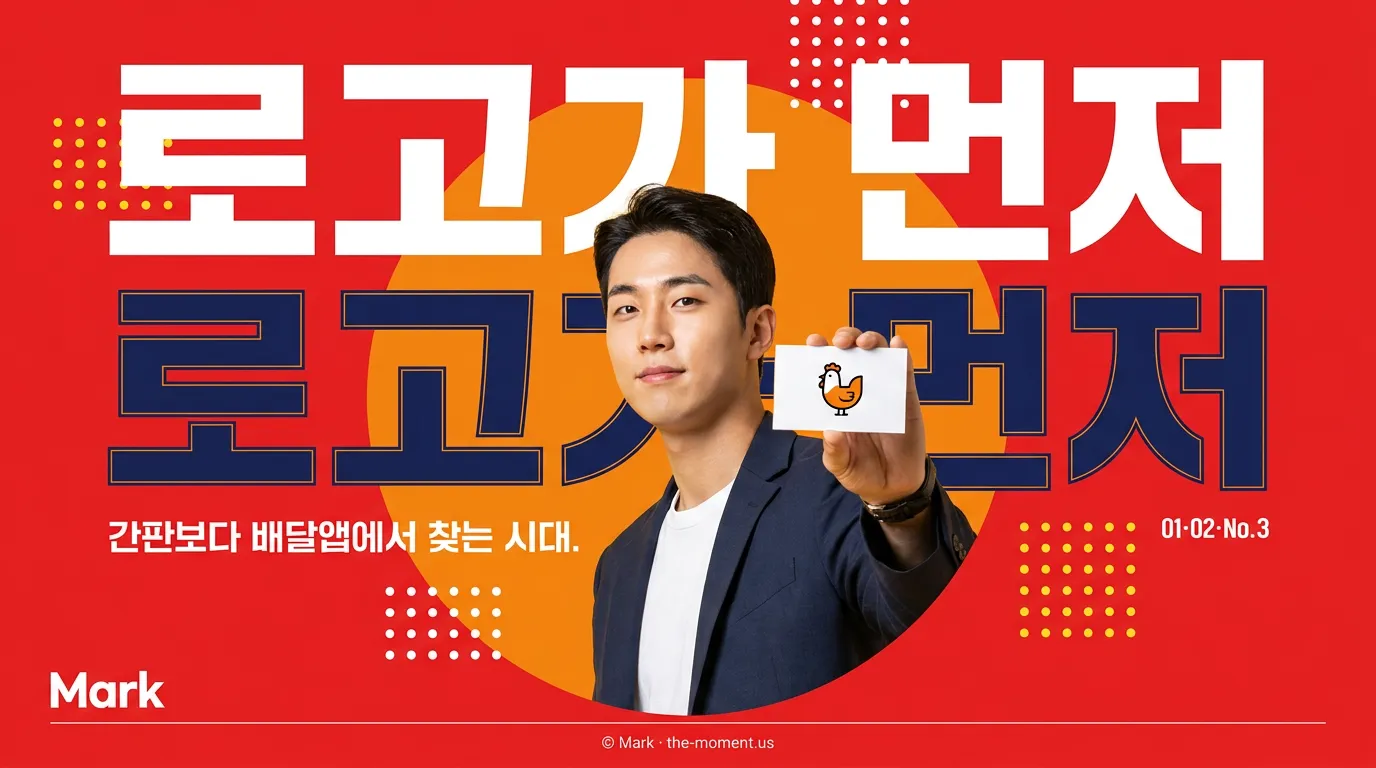
치킨집 간판 디자인, 빨간색 전에 로고부터 잡아야 하는 3가지
치킨집 간판 디자인을 색깔·폰트보다 로고와 브랜드 기준으로 다시 정리했습니다. 사장님이 먼저 정할 3가지만 봅니다.
밤 9시, 손님은 간판 글자를 읽기 전에 배달앱에서 본 로고인지부터 찾습니다.
빨간 간판이면 정말 치킨집처럼 보일까요?
저라면 색부터 고르지 않습니다. 먼저 ‘우리 치킨이 어떤 장면에서 먹히는지’부터 정합니다. 퇴근 후 맥주와 먹는 치킨인지, 아이 있는 집이 주말에 시키는 치킨인지, 혼자 먹는 순살 박스인지에 따라 로고의 표정이 달라집니다.
빨간색은 치킨집에서 너무 많이 씁니다. 그래서 눈에 띄는 색이 아니라, 오히려 묻히는 색이 될 때가 많습니다. 문제는 빨강 자체가 아닙니다. 빨강을 쓰더라도 ‘불맛’, ‘레트로 통닭’, ‘바삭한 크런치’ 중 무엇을 말하는 빨강인지 정하지 않은 게 문제입니다.
최근 공정거래위원회 가맹사업 현황을 다룬 연합뉴스 기사에서 2024년 치킨 가맹점 평균 매출액은 5.2% 늘었지만, 가맹점 수는 3.2% 줄었다는 대목이 보였습니다. 저는 이걸 이렇게 봅니다. 치킨 수요는 남아 있지만, 애매한 가게가 버티기 어려워졌다는 뜻입니다. 그래서 치킨집 간판 디자인은 ‘빨간색으로 크게’가 아니라 ‘한 번 보고 기억나는 브랜드’에서 시작해야 합니다.
폰트는 두꺼우면 충분할까요?
사장님, 간판 글씨가 두꺼운 것과 브랜드가 또렷한 건 다릅니다. 두꺼운 폰트는 멀리서 보일 수는 있어도, 맛의 인상까지 남기지는 못합니다. ‘바삭’, ‘숯불’, ‘옛날’, ‘프리미엄’, ‘가성비’가 같은 글씨로 보이면 손님은 가격만 봅니다.
폰트는 이름의 말투입니다. ‘바사삭연구소’ 같은 이름에 궁서체를 쓰면 이상하고, ‘철판마늘통닭’에 너무 얇은 산세리프를 쓰면 힘이 빠집니다. 저는 치킨집 로고를 볼 때 획의 끝을 먼저 봅니다. 끝이 둥글면 친근하고, 각지면 튀김옷이 딱딱 끊기는 느낌이 납니다. 이 작은 차이가 메뉴판, 배달앱 썸네일, 포장 박스에서 계속 반복됩니다.
로고가 간판보다 먼저 나와야 하는 이유는 뭘까요?
간판은 로고가 붙는 자리 중 하나입니다. 그런데 현장에선 순서가 자주 거꾸로 갑니다. 간판 업체에 먼저 가서 시안을 받고, 그 안에 가게 이름을 얹습니다. 그러면 배달앱 아이콘, 네이버 플레이스, 포장지, 유니폼이 전부 따로 놀기 쉽습니다.
저라면 먼저 세 가지를 고정합니다. 이름의 길이, 심볼의 모양, 대표 색 하나. 그다음에 간판 크기와 조명 방식을 맞춥니다. 특히 치킨집은 ‘닭 그림’을 꼭 넣어야 한다는 압박이 있는데, 닭을 넣을수록 평범해지는 경우가 많습니다. 뼈, 집게, 튀김 조각, 맥주 거품, 소스 방울처럼 메뉴 경험에서 나온 심볼이 더 오래 갑니다.
마크에서 치킨집이나 음식점 브랜드를 잡을 때도 간판 시안부터 만들지 않습니다. 작은 앱 아이콘에서 알아보이는지, 검은 봉투에 흰색 한 색으로 찍어도 버티는지, 야간 간판에서 획이 뭉개지지 않는지 먼저 봅니다. 로고가 작게 살아야 크게 붙였을 때도 버팁니다.
그럼 색깔은 몇 개가 적당할까요?
대표 색은 하나, 보조 색은 많아도 둘이면 됩니다. 치킨집은 이미 메뉴 사진이 노랗고 붉습니다. 여기에 로고까지 색이 많으면 화면이 지저분해집니다. 특히 배달앱에서는 메뉴 사진, 할인 배지, 별점, 리뷰 숫자가 한 화면에 붙습니다. 로고는 거기서 조용히 또렷해야 합니다.
추천은 간단합니다. 바탕색 하나를 정하고, 글자색 하나를 고정하세요. 예를 들면 짙은 밤색 바탕에 크림색 글자, 딥레드 바탕에 아이보리 글자, 블랙 바탕에 옐로 포인트처럼요. 핵심은 예쁜 조합이 아니라 반복 가능한 조합입니다. 간판, 메뉴판, 쿠폰, 배달 봉투에 매번 같은 인상이 남아야 합니다.
특허청의 상표 안내에서도 출원 전 같은 이름이나 비슷한 이름을 키프리스에서 찾아보라고 설명합니다. 색과 폰트를 다 정해놓고 나중에 이름이 막히면 처음부터 다시 가야 합니다. 치킨집 로고를 만들기 전에 브랜드명 검색부터 하는 이유가 여기에 있습니다.
지금 무엇부터 바꾸면 될까요?
새 간판 견적을 받기 전에, 지금 쓰는 이름을 3cm짜리 원 안에 넣어보세요. 배달앱 아이콘 크기입니다. 안 읽히면 간판을 키워도 해결되지 않습니다. 이름이 길면 줄이고, 심볼이 복잡하면 덜어내고, 색이 많으면 하나만 남기면 됩니다.
치킨집 간판 디자인은 매장 앞 판을 꾸미는 일이 아닙니다. 손님 머릿속에 ‘아, 거기’ 하고 저장될 모양을 정하는 일입니다. 그 모양이 로고이고, 간판은 그 로고가 밤거리에서 일하는 방식입니다.
오늘 할 일은 하나입니다. 가게 이름, 대표 메뉴, 쓰고 싶은 색 1개를 적고 “이 세 가지가 한 브랜드처럼 보이나?”를 먼저 확인하세요.